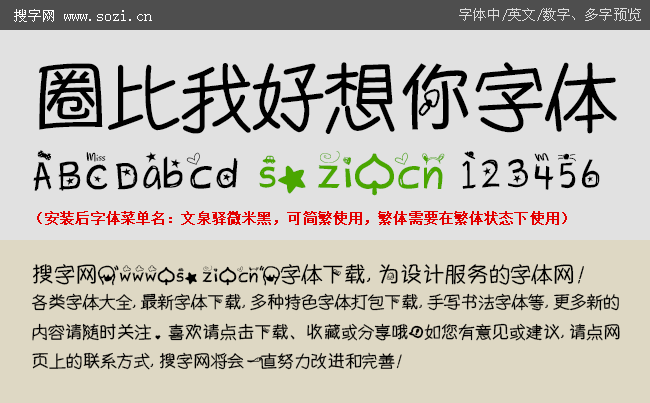
圈比我好想你字體
搜字網(wǎng)給大家提供一款很卡通的手機中文字體下載。修改者將它命名為圈比我好想你字體,這款手機字體是仿照兒童手寫風(fēng)格的卡通手寫字體,結(jié)構(gòu)帶有POP字體風(fēng)格,字體間還配上了非常有趣的卡通圖案,特別適合喜歡手機字體個性一些的朋友在手機上安裝使用。